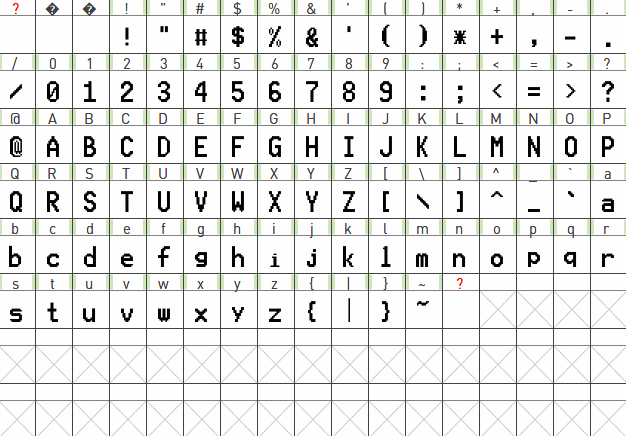
bitMatrix-E1
bitMatrix-E1 family fonts are often used by some banks to print the POS receipts. Sometimes they are used for Australia GM Cabs receipts.
Contoh hasil cetak 1:
Contoh hasil cetak 2:
Contoh hasil cetak 3:
Contoh hasil cetak 4 (AXIS Bank) (①bitMatrix-E1 ②bitMatrix-E1-narrow):
Contoh hasil cetak 5 (①bitMatrix-E1-wide ②bitMatrix-E1):
Contoh hasil cetak 6 (Citibank) (①bitMatrix-E1 ②bitMatrix-E1-narrow):
Contoh hasil cetak 7:
Contoh hasil cetak 8 (①bitMatrix-E1-narrow):
Contoh hasil cetak 9 (①bitMatrix-E1-narrow):
Contoh hasil cetak 10 (①bitMatrix-E1-narrow):
Contoh hasil cetak 11 (KBank) (①bitMatrix-E1-wide):
Contoh hasil cetak 12 (①bitMatrix-E1-wide):
Contoh hasil cetak 13 (Bradesco):
Contoh hasil cetak 14 (Bradesco):
Contoh hasil cetak 15 (Santander):
Contoh hasil cetak 16 (①bitMatrix-E1-wide):
Contoh hasil cetak 17 (①bitMatrix-E1-narrow):
Contoh hasil cetak 18 (①bitMatrix-E1-wide ②bitMatrix-E1):
Contoh hasil cetak 19 (①bitMatrix-E1-wide ②bitMatrix-E1):
Contoh hasil cetak 20 – Australia GM Cabs taxi receipt (①bitMatrix-E1-wide ②bitMatrix-E1):
Contoh hasil cetak 21 – Australia GM Cabs taxi receipt (①bitMatrix-E1 ②bitMatrix-E1-wide):
Semua karakter font bitMatrix-E1:
Font bitMatrix-E1 dilihat dengan penampil font bawaan Windows: